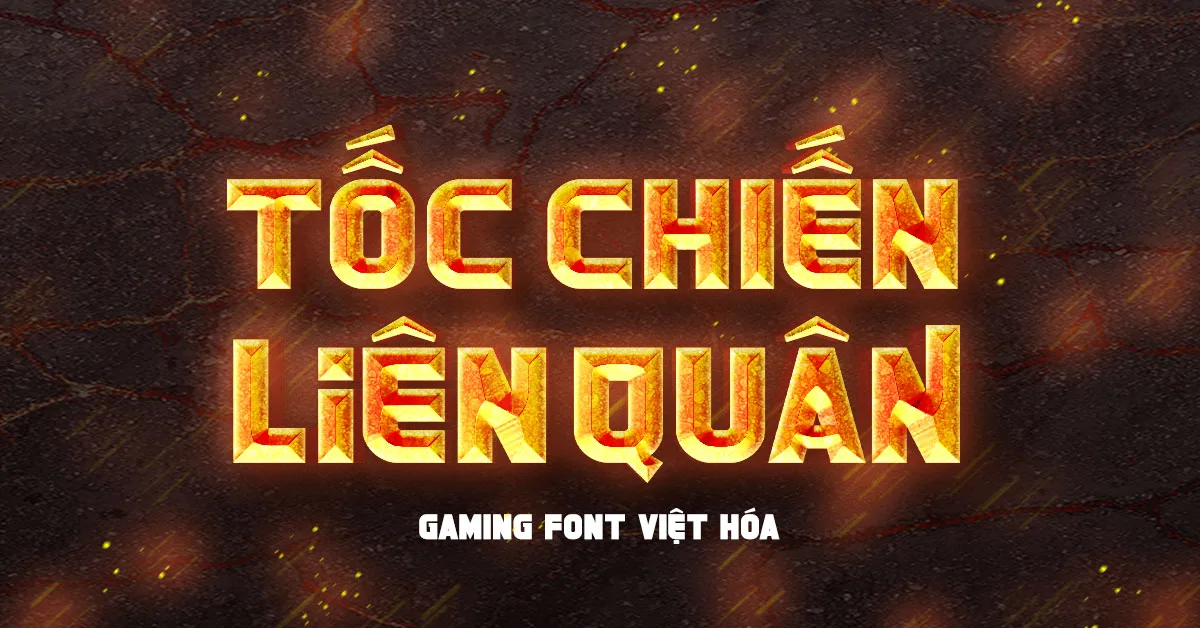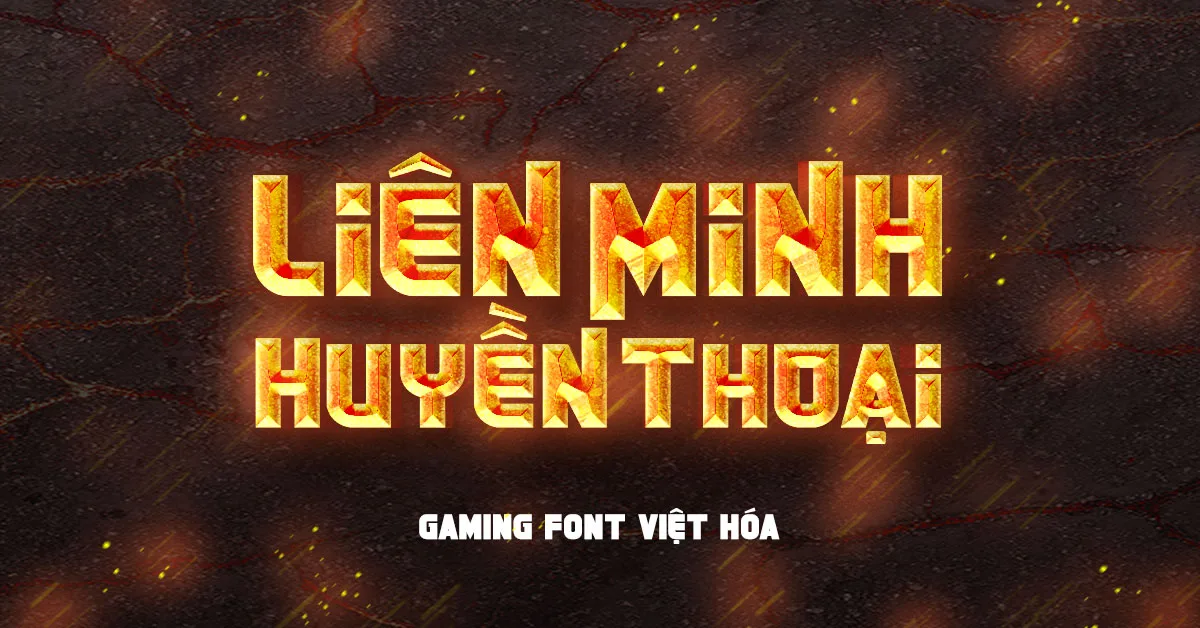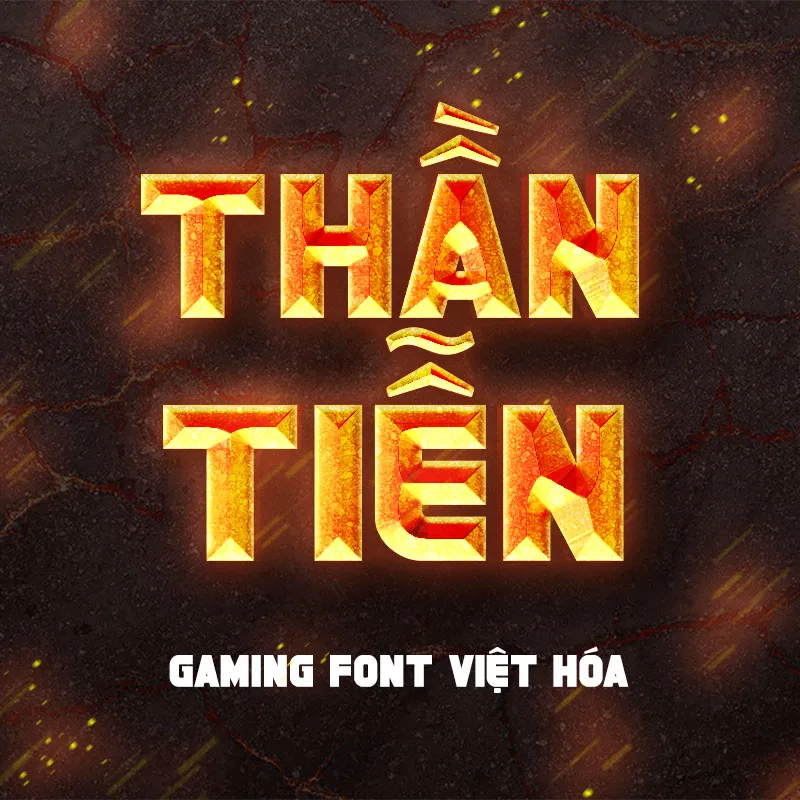
Font Fz Futurik Việt Hóa
Tải Font Fz Futurik Việt Hóa – Phông chữ Gaming cực hot
Font Fz Futurik Việt Hóa là một phông chữ độc đáo, được thiết kế dành riêng cho các dự án liên quan đến game, đồ họa và thiết kế sáng tạo. Với kiểu dáng hiện đại, mạnh mẽ và đầy cá tính, Fz Futurik dễ dàng thu hút sự chú ý từ cái nhìn đầu tiên. Các đường nét của phông chữ này rất sắc sảo, kết hợp giữa yếu tố kỹ thuật số và sự tinh tế, mang lại cảm giác mạnh mẽ và phù hợp với các tựa game đòi hỏi sự hành động và kịch tính.
Fz Futurik đã được Việt hóa hoàn toàn, hỗ trợ đầy đủ các ký tự tiếng Việt với dấu sắc nét và dễ đọc, giúp người dùng thoải mái sử dụng trong các dự án nội dung tiếng Việt. Điều này làm cho Fz Futurik trở thành sự lựa chọn hoàn hảo cho các nhà thiết kế đồ họa, các streamer, hoặc bất kỳ ai muốn tạo ra những nội dung mang phong cách game độc đáo, thu hút và ấn tượng.